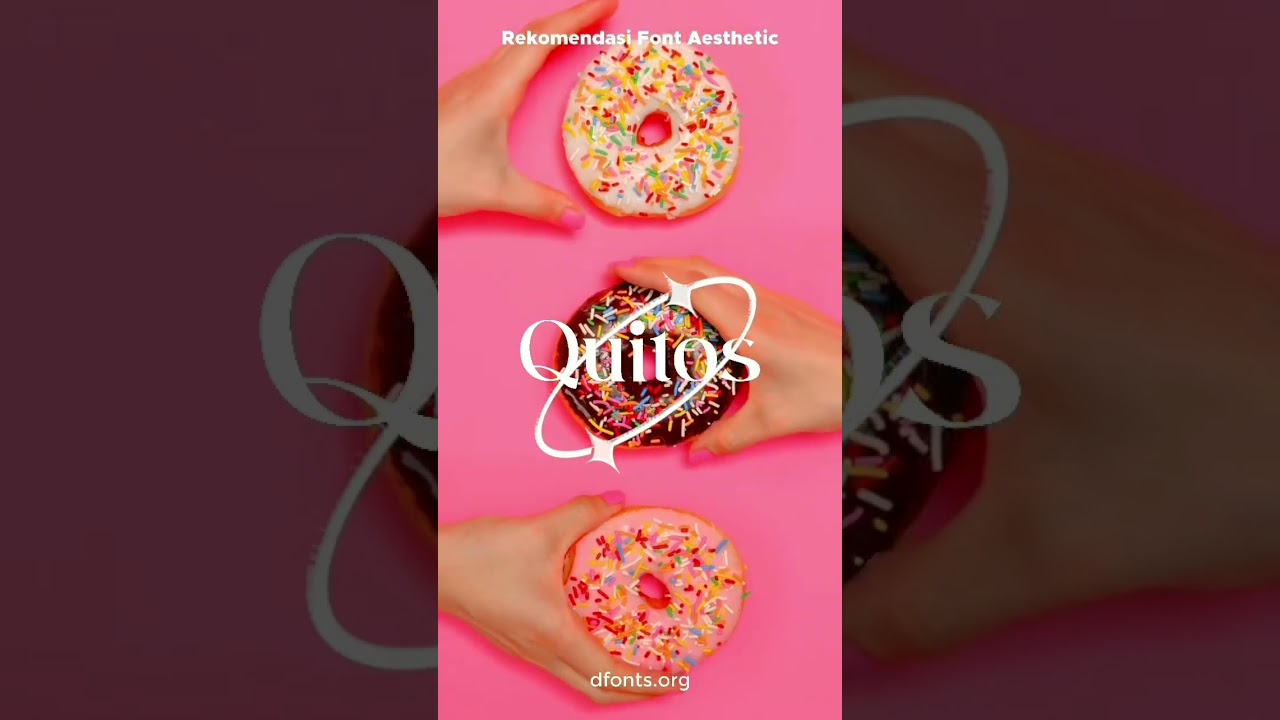
10 Ide Rekomendasi Fonts Huruf Tipografi Inspirasi Tipografi 6 nov 2023 jelajahi papan "rekomendasi fonts" milik nayaa🦋 di pinterest. lihat ide lainnya tentang huruf tipografi, inspirasi tipografi, tipografi. Ada beberapa tipografi yang harus dimiliki oleh desainer grafis, yang bisa digunakan untuk membuat desain semakin menarik.
Rekomendasi Font Di 2025 Jenis Huruf Tulisan Huruf Tipografi Seni Rupa rupanya ada 10 jenis tipografi yang anda boleh guna sebagai font jenama atau font brand bisnes anda. ini senarainya. baca di sini. Cari font gratis berkualitas? temukan 25 font gratis terbaik untuk berbagai proyek desain anda dalam panduan tipografi modern 2025 ini. Tipografi adalah seni dan teknik dalam pengaturan huruf huruf agar terlihat menarik dan mudah dibaca. dalam desain grafis, pemilihan tipografi yang tepat dapat memberikan kesan dan makna yang berbeda pada suatu karya. Pernah melihat gambar tipografi? adakah di antara karya tersebut yang mampu menumbuhkan inspirasi juga semangat saat ini? yuk cari tahu jawabannya dalam artikel finansialku berikut ini.
Inspirasi Tipografi adalah seni dan teknik dalam pengaturan huruf huruf agar terlihat menarik dan mudah dibaca. dalam desain grafis, pemilihan tipografi yang tepat dapat memberikan kesan dan makna yang berbeda pada suatu karya. Pernah melihat gambar tipografi? adakah di antara karya tersebut yang mampu menumbuhkan inspirasi juga semangat saat ini? yuk cari tahu jawabannya dalam artikel finansialku berikut ini. Di bawah ini, anda akan menemukan 20 jenis font keren yang menarik untuk dicoba, baik untuk penggunaan pribadi maupun dalam proyek web dan desain grafis berikutnya. dan tak perlu cemas, kami telah menyertakan opsi font, termasuk yang gratis dan berbayar!. Temukan gaya tipografi yang unik, mulai dari serif klasik hingga sans serif yang minimalis. sertai kami dalam perjalanan merangkai huruf huruf artistik yang menarik perhatian. telusuri contoh contoh tipografi menakjubkan yang dapat diaplikasikan dalam logo, poster, dan berbagai proyek kreatif anda. Dalam dunia desain grafis, tipografi bukan sekadar tentang menyusun huruf agar bisa dibaca, melainkan seni menyampaikan emosi dan karakter melalui bentuk tulisan. pemilihan jenis huruf (font) yang tepat dapat mengubah pesan yang biasa saja menjadi karya visual yang kuat dan berkesan. Sedang mencari font tipografi yang keren dan minimalis untuk desain? cek daftarnya di sini, download dan unduh secara gratis!.